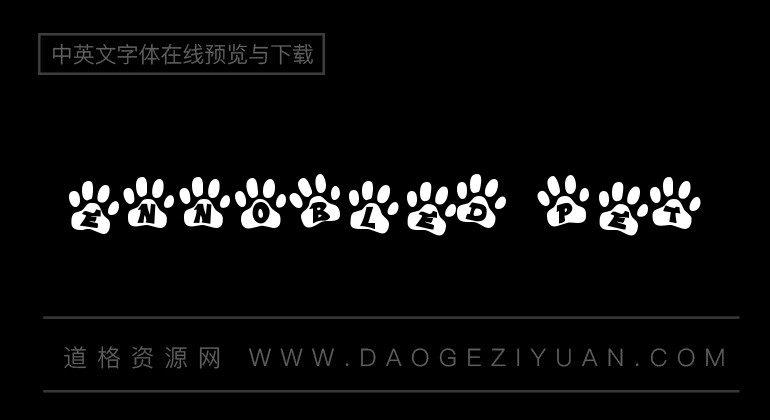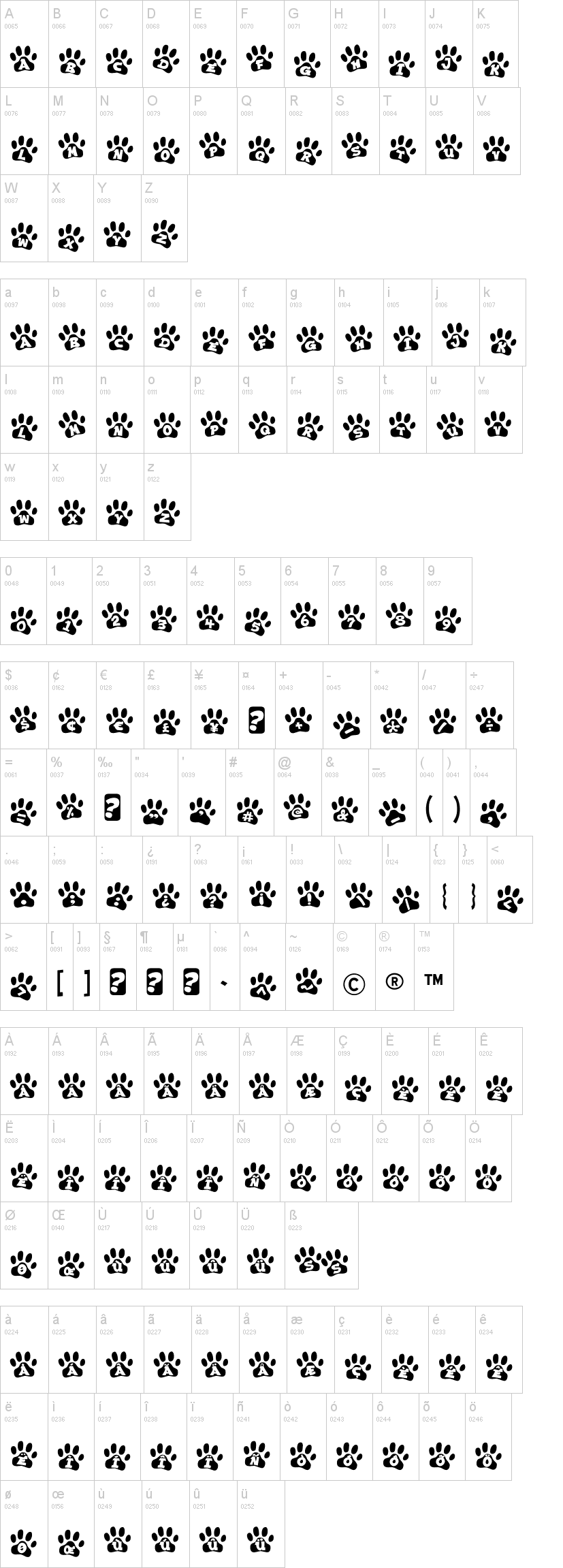
Ennobled Pet
Ennobled Pet是一款可爱的手写字体,它的设计灵感来自于宠物和小动物。这种字体的特点是每个字母都有一些小动物的元素,例如字母“a”可能会有一只小狗的耳朵,字母“b”可能会有一条小尾巴,整个字母风格非常生动活泼。 Ennobled Pet字体适用于卡通、插画、儿童图书等设计领域,可以为设计作品增添一份可爱和温馨的氛围。此外,它也可以用于制作明信片、海报、贺卡等场合,为文字内容带来一份独特的表现形式。
Ennobled Pet是一款非常不错的手写艺术字体,具有很好的视觉感,适合于文化类的宣传设计、商业类品牌的广告和产品包装设计以及个性化文字排版等较多场景。